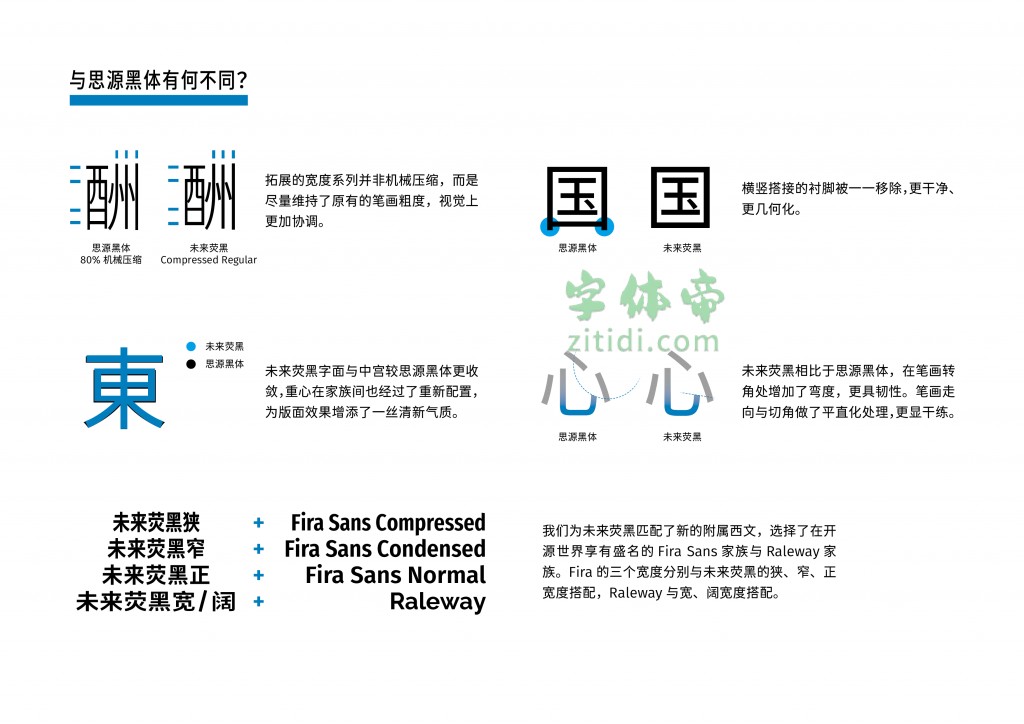
未来荧黑字体,免费可商用,9字重满足你的更多需求!字体推荐
未来荧黑是一个基于思源黑体、Fira Sans和Raleway的开源字体项目,支持简体中文、繁体中文与日文;思源黑体的7字重被扩展为9字重,并提供了宽度系列,全家族共44款字体。
相比于思源黑体,未来荧黑的造型更加简明现代,版面效果清新轻快。未来荧黑的中宫与字面更加收敛,重心在字重之间经过了重新配置;笔画细节上处理得更加干练,简洁而平直化。您可以下载样张来预览未来荧黑的设计。
未来荧黑的实现介于参数化与轮廓滤镜,使用了图像处理算法对字形建模。字体的制作并没有借助字体设计软件,而是用一个Web实现的可视化调参工具来确定字体参数。
我们为未来荧黑开发了一个在线演示,同时它是未来荧黑修改字体参数的可视化交互环境。你可以在这里通过改变各种参数来修改文字样貌,导出的参数可用于字体构建。